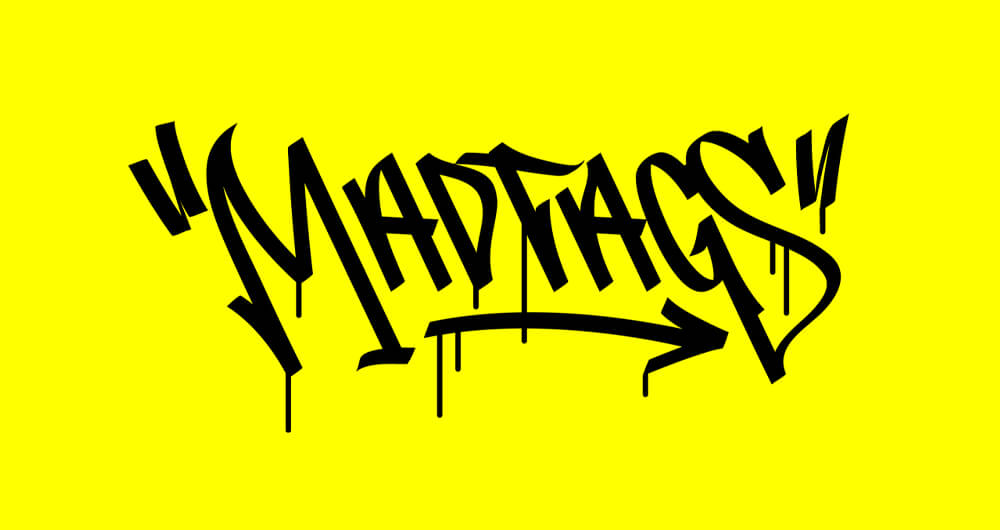
Ob für Poster, Logos oder digitale Designs: Eine passende Graffiti Schrift bringt den typischen Stil urbaner Street-Art in kreative Projekte. Die Auswahl reicht von klassischen Tags bis hin zu modernen Brush-Fonts. In dieser Übersicht finden sich kostenlose Graffiti Schriften sowie kommerziell nutzbare Fonts für verschiedenste Einsatzzwecke.
Graffiti Schrift im Street Art Stil zum Downloaden. (Die Abbildung zeigt die Schriftart Urban Gear von Cikareotype.)
Graffiti Schriftarten für Plakate, Logos und mehr
Graffiti Sprayer mit urbaner Typografie
Graffiti ist kreativ, bunt und expressiv. Die häufigsten Formen – etwa das Graffiti-Writing oder Style-Writing – sind fester Bestandteil der Hip-Hop-Kultur. Auch Techniken wie Scratching oder Etching haben den Look vieler Graffiti Schriften geprägt.
Die Bandbreite reicht von Fonts, die sich eng an klassische Schriftzüge von Sprayern anlehnen, bis zu solchen, die den Stil abstrahieren und neu interpretieren. Einige der hier vorgestellten Graffiti Fonts stehen kostenlos zur Verfügung, andere sind kommerziell nutzbar.
Graffont: Graffiti Schriften im handgeschriebenen Look
Die Plattform Graffont hat sich auf handgeschriebene Graffiti Fonts spezialisiert. Hier stehen verschiedene Schriftarten zur Auswahl, die sich für digitale Designs, Poster oder urbanes Branding eignen. Einige Fonts sind kostenlos erhältlich, andere können für kommerzielle Zwecke lizenziert werden. Besonders auffällig sind die drei Hauptfonts, die unterschiedliche Stile und Einsatzzwecke abdecken:
Graffont: Graffiti Schriften im handgeschriebenen Look
MadTags Graffiti Schrift
MadTags
MadTags ist ein Font, der den direkten Stil von Street-Art aufgreift. Mit vier Schriftschnitten und über 300 Zeichen bietet die Schriftfamilie reichlich Spielraum für Gestaltung. Der Stil ist wild, urban und authentisch – perfekt für Plakate, Verpackungen oder digitale Projekte mit Charakter. Eine abgespeckte Version steht kostenlos zur Verfügung.
BlackTop Graffiti Schrift
BlackTop
BlackTop ist eine handgezeichnete Graffiti-Schrift von SixAbove Studios. Der Display-Font lässt sich auch in engen Layouts gut einsetzen. Der freie Demo-Font darf privat genutzt werden. Für kommerzielle Nutzung ist eine Lizenz ab ca. 6 Dollar erhältlich.
Crooklyn Brush Graffiti Font
Crooklyn Brush
Die Schrift Crooklyn Brush wurde vom Rap-Umfeld und urbaner Ästhetik inspiriert. Die fließenden Buchstaben erinnern an Marker-Linien, ergänzt durch passende Vektorelemente. Ideal für Mode, Musikdesign oder Statements im Street-Style. Erhältlich ab 12 Dollar inklusive Extras.
Weitere Graffiti Schriften zum Download
Don Graffiti Schrift
Don Graffiti
Don Graffiti von Don Marciano ist eine klassische Graffiti-Schrift mit 197 Zeichen im Opentype-Format. Die Schrift lässt sich nach dem Prinzip „Pay what you want“ erwerben – auch kostenlos.
JFK Wall Hunter Graffiti Schrift
JFK Wall Hunter
Die Schrift JFK Wall Hunter wurde von weltweiten Street-Art-Szenen inspiriert. Der mit Marker gezeichnete Stil eignet sich für urbane Illustrationen. Die Demo-Version ist kostenlos, die Vollversion ab 14 Dollar erhältlich.
BlowBrush Graffiti Schrift
BlowBrush
Der kostenlose Font BlowBrush stammt vom serbischen Designer Petar Acanski. Die Schrift im Marker-Stil ist sowohl für private als auch kommerzielle Nutzung freigegeben.
Skylight Graffiti Schrift
Skylight Graffiti
Skylight Graffiti von Rvq Type Foundry enthält viele dekorative Extras wie Sonderzeichen und alternative Buchstabenformen. Der Font kann für 15 Dollar erworben werden.
Graffiti Fat Font
Graffiti Fat Font ist ein moderner SVG-Font von dansdesign mit hohem Wiedererkennungswert. Die Inspiration stammt von alten Schildern. Preis: ab 14 Dollar.
Tag Type Free Graffiti Font
Tag Type
Tag Type wurde vom ukrainischen Designer Andy Panchenko entwickelt. Der Font im urbanen Stil steht kostenlos für den privaten Gebrauch zur Verfügung.
Urban Gear Graffiti Font
Urban Gear
Urban Gear ist ein extrudierter Graffiti-Font von Cikareotype. Mit seinem 3D-Effekt und handgezeichnetem Look eignet sich die Schrift besonders für aufmerksamkeitsstarke Designs mit urbanem Charakter. Enthalten sind Solid-, Outline- und Extrude-Versionen. Die Version für private Zwecke steht kostenlos zum Downloaden bereit.
Lazy Street Graffiti Font
Lazy Street
Lazy Street von Cikareotype kombiniert einen lässigen Graffiti-Stil mit soliden Linien. Die Schriftart bietet Varianten in Solid, Outline und Extrude – perfekt für typografische Experimente mit Street-Art-Flair. Für private Nutzung ist die Schrift kostenlos.